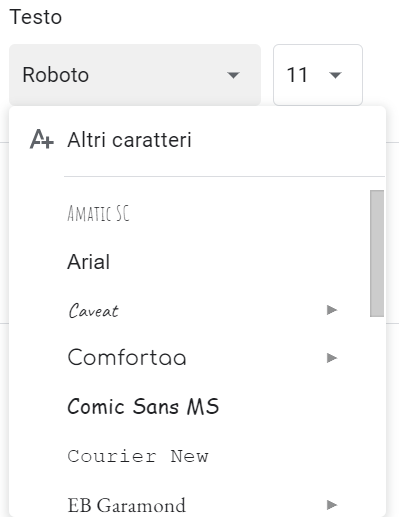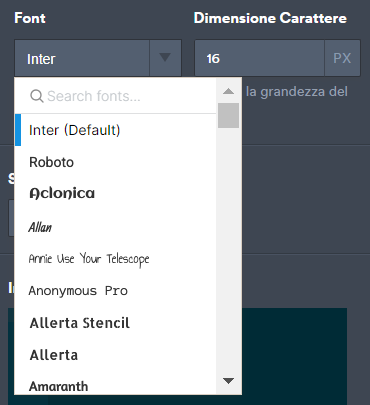
Moduli Google è uno strumento semplice. Originariamente era stato progettato per essere un componente aggiuntivo di Fogli Google, ma nel 2016 è diventato un’applicazione indipendente.
Nel corso del tempo ha incorporato nuove caratteristiche, che però hanno fornito funzionalità limitate. Google ha lavorato di più sulle sue offerte principali, come Fogli e Documenti, che su strumenti come Moduli.
Quindi, anche se è possibile modificare la dimensione dei caratteri su Moduli Google, non ci si deve entusiasmare troppo. Ma continua a leggere e vedrai che, sebbene le opzioni siano limitate, esiste una soluzione e alcuni componenti aggiuntivi in grado di fornirti più opzioni.
Cambiare i caratteri tramite le impostazioni integrate di Google
Moduli Google offre una serie di opzioni per personalizzare e progettare i moduli, ma poiché questo articolo si concentra sui caratteri, non le esamineremo.
Sei una persona intelligente. Tutte le impostazioni del design sono in un unico posto e puoi curiosare dopo aver individuato la sezione per i caratteri.
Sul lato destro della pagina si aprirà un menu di opzioni per il tema. Le impostazioni per il carattere si trovano in fondo all’elenco. Vedrai che avrai a disposizione una vasta gamma di caratteri con cui sbizzarrirti.
Cerca di non perdere la testa per la quantità di opzioni disponibili. Puoi trovare un font serif generico e un sans-serif generico, che sono abbastanza gradevoli. C’è anche Playful, che si avvicina al Comic Sans e Decorative, impossibile da leggere per i minori di 20 anni.
Utilizzare un componente aggiuntivo
La migliore opzione per ottenere più caratteri è utilizzare un componente aggiuntivo. Sfortunatamente, ce n’è solo uno disponibile, che elimina completamente lo stile di Moduli Google dall’equazione.
Formfacade funziona egregiamente, ma non offre alcuna funzionalità in più. Si appoggia semplicemente a Moduli Google e lo rende esteticamente più bello.
Si accede così al sito web di Formfacade, dove è possibile progettare il design del modulo. Per modificare il carattere, fare clic sull’ingranaggio accanto al titolo del modulo.
Dal menù delle impostazioni sulla destra, selezionare la scheda Fonts.
L’approccio migliore: Una soluzione alternativa
Come detto all’inizio, Moduli Google è davvero semplice. Se sei arrivato fino a questo punto, probabilmente non sei soddisfatto delle opzioni disponibili. Quindi cos’altro si può fare?
A volte la soluzione migliore è rinunciare, non alla creazione di moduli, ovviamente. Forse però è arrivato il momento di abbandonare Moduli Google. Il numero di caratteri è solo l’inizio dei limiti di questa piattaforma.
Jotform è un costruttore di moduli senza limitazioni. E non si tratta di un’affermazione arrogante. Jotform ha il maggior numero di funzioni di qualsiasi altro strumento per la creazione di moduli sul mercato. Inoltre, chiunque sia abbastanza intelligente da farlo può aggiungere nuovi widget a Jotform.
Ma che dire dei font? Jotform ne ha a decine incorporati e la scelta è molto semplice.
E se sei molto esigente e non riesci a trovare nulla di tuo gradimento in quell’elenco? Puoi inserire codici CSS direttamente nel tuo modulo e importare font. Puoi anche controllare ogni aspetto del layout con il nostro Designer Avanzato.